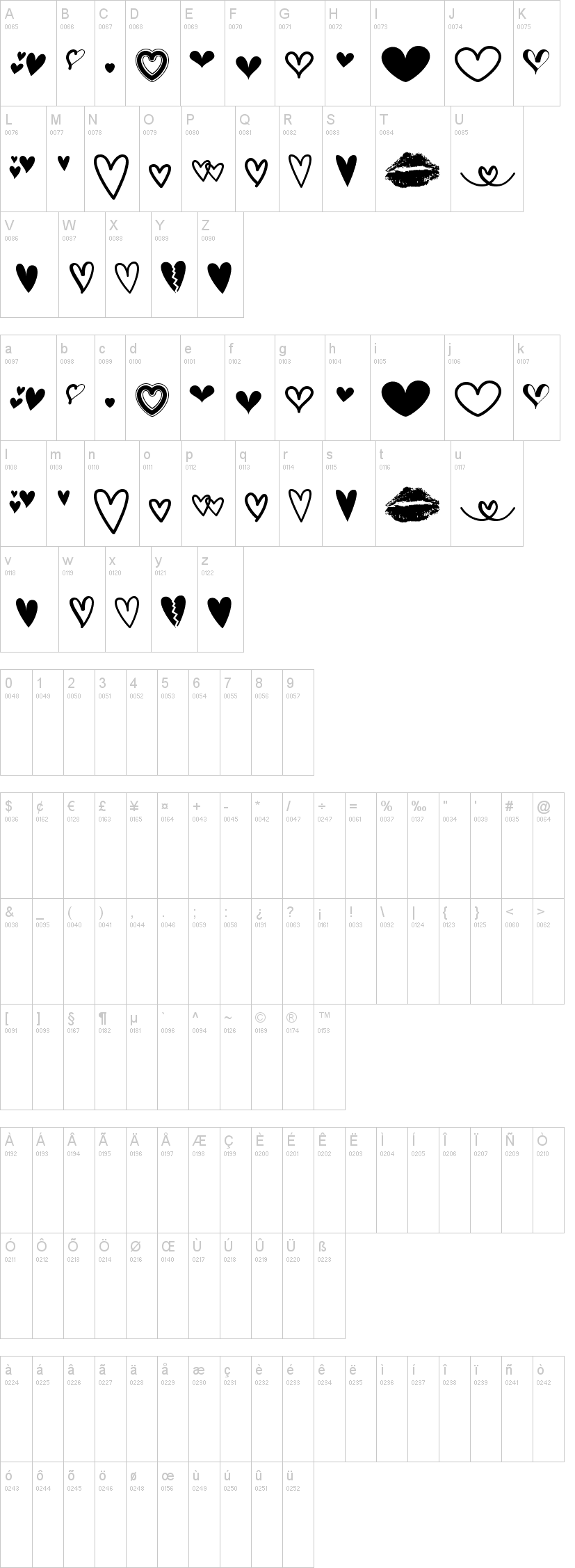
MF Love Dings 2 是一种装饰性字体,它由 Misti's Fonts 设计。它包含了许多带有爱心和其他装饰图案的符号和符号组合,可以用于各种场合,特别是与爱情和浪漫有关的设计。这个字体适用于制作贺卡、海报、宣传册、婚礼邀请函等设计。 该字体是一种 TrueType 字体,可以在 Windows 和 Mac OS X 操作系统中使用,并且可以在 Adobe Photoshop、Illustrator 和 InDesign 等设计软件中使用。字体文件可以从 Misti's Fonts 官网或其他字体下载网站上免费下载。内容介绍
MF Love Dings 2是一款非常不错的手写艺术字体,具有很好的视觉感,适合于文化类的宣传设计、商业类品牌的广告和产品包装设计以及个性化文字排版等较多场景。